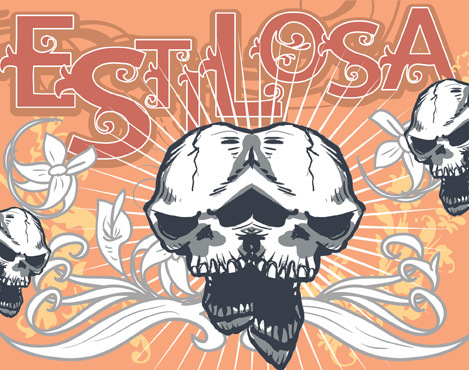
VTKS Estilosa von Douglas Vitkauskas ist eine kostenlose, verschnörkelte Display-Schrift mit theatralischem Flair im Art-Nouveau-Stil. Die Großbuchstaben kombinieren robuste, blockartige Formen mit geschwungenen Verzierungen und Haken – dadurch wirkt die Schrift auf den ersten Blick kräftig, bricht aber immer wieder in Ornamentik auf.
Ideal für Poster-Überschriften, Boutique-Branding, Event-Flyer, Musik-Cover und Titelkarten, bei denen ein Hauch von Eleganz die Stimmung bestimmt. Da sie kostenlos ist, eignet sie sich zudem hervorragend für Monogramme, Initialen oder kurze Verpackungsdesigns, denn die wiederkehrenden Schnörkel verleihen selbst wenigen Buchstaben enorme Präsenz.